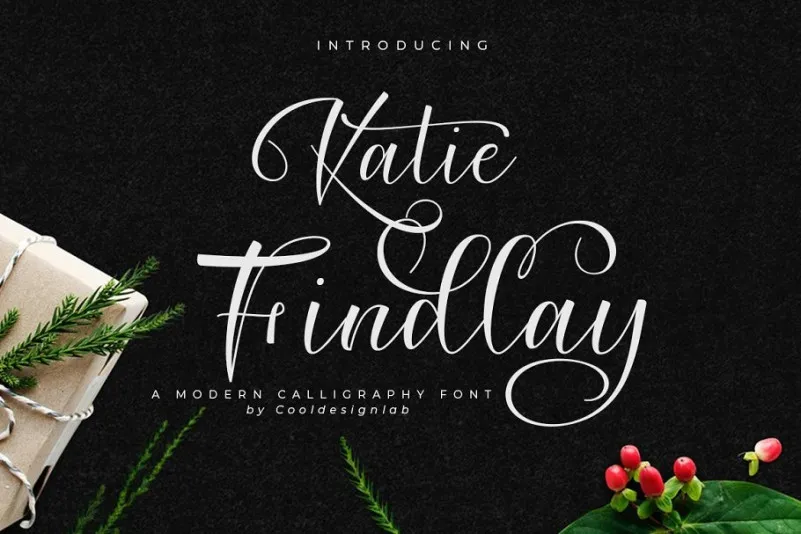
Katie Findlay Script Font – Fonte Grátis
Katie Findlay Script Font
Descubra a beleza única e sofisticada da Katie Findlay Font — uma obra-prima criada por 24Design. Este script elegante é perfeito para estilos modernos, oferecendo uma conexão cuidadosamente estabelecida entre cada letra. A fonte possui altas ascenderes que adicionam ornamentos distintivos às letras diferentes. Ideal para design de cartões de agradecimento, materiais de marca, cartões de empresa, citações e panfletos, esta fonte moderna é projetada com habilidade meticulosa. Ela se adequa perfeitamente a uma variedade de aplicativos gráficos. A Katie Findlay Script inclui um conjunto completo de letras maiúsculas e minúsculas, números e sinais gráficos, assim como todos os pontos do alfabeto internacional em tamanho grande. Todas as letras minúsculas contêm início e término da carga. Além disso, também oferece alternativas para letras maiúsculas e símbolos multilíngues. A fonte foi codificada usando Unicode PUA, permitindo acesso completo a todos os caracteres adicionais sem necessidade de software especializado. A Katie Findlay Font é uma escolha ideal para quem busca um estilo elegante e moderno em seus projetos gráficos.